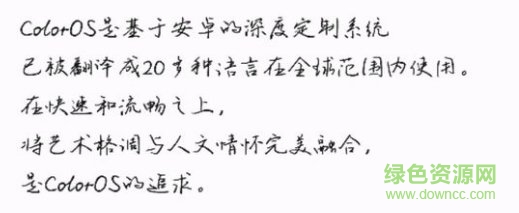
Aa以夢為馬字體給人一騎紅塵江湖肆意的安穩(wěn)現(xiàn)世質感,字里行間都是一股淡泊灑脫的江湖氣息,讓你無處安放的心找到一處歸宿,以夢為馬莫負韶華,來綠色資源網(wǎng)擁有它吧!
忽晴忽雨的江湖,愿你以夢為馬,隨處可棲。
以夢為馬,指把自己的夢想作為前進的方向和動力。馬,在這里是指動力,亦有希望的意思。以馬這種強健美好的動物作為希望的載體,承載內心的理念和夢想,為未來的人生提供內在支持。
該字體彰顯了恣意灑脫的豪杰之氣,給人撲面而來的張揚質感,藝術效果十分出色,運用在海報設計、平面設計等場合均可!